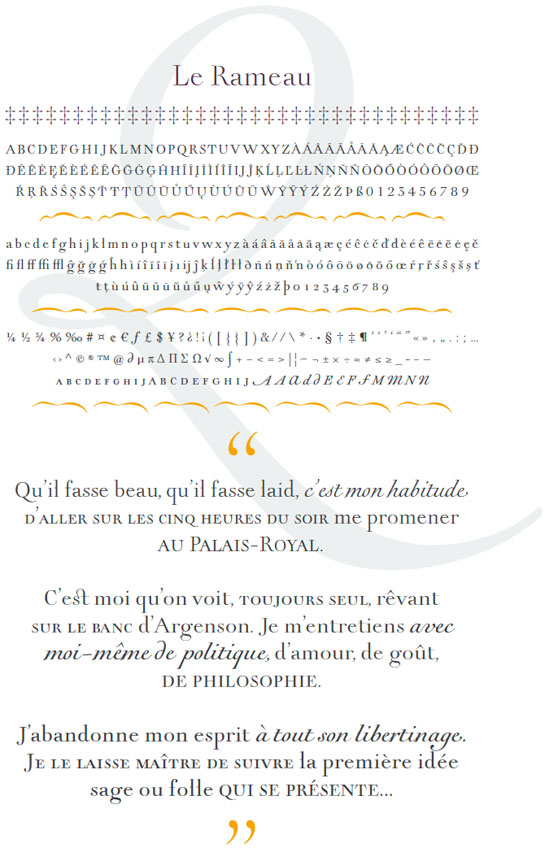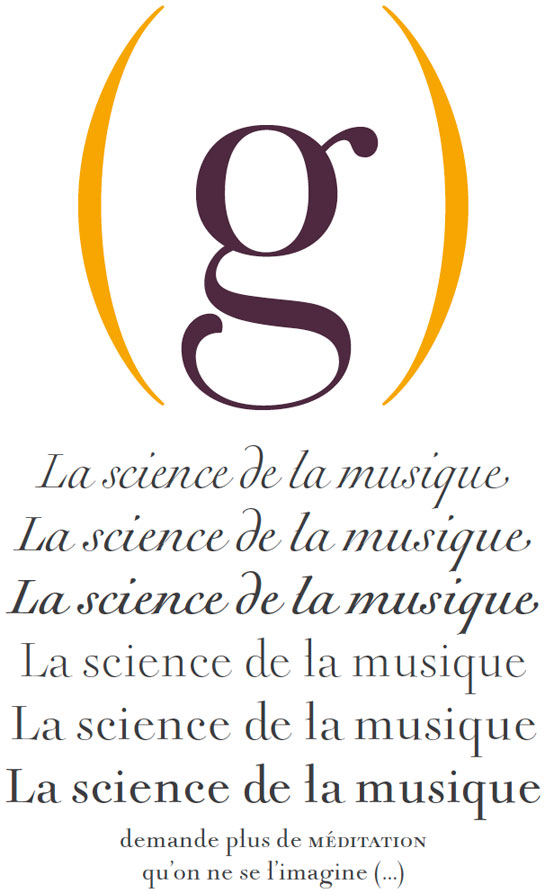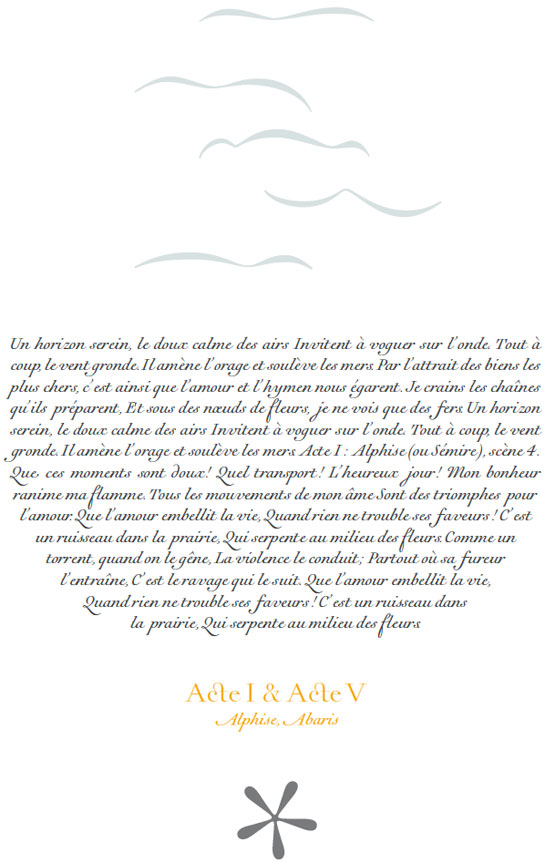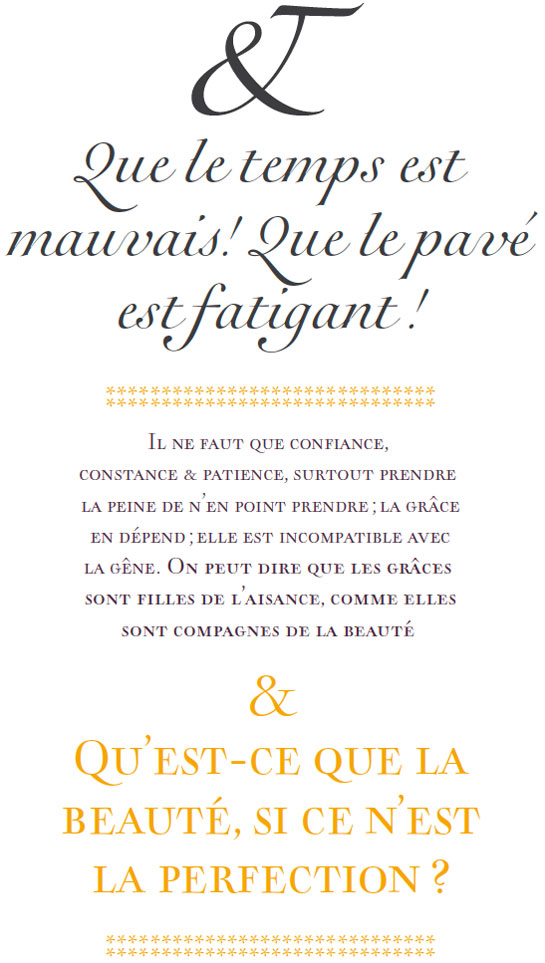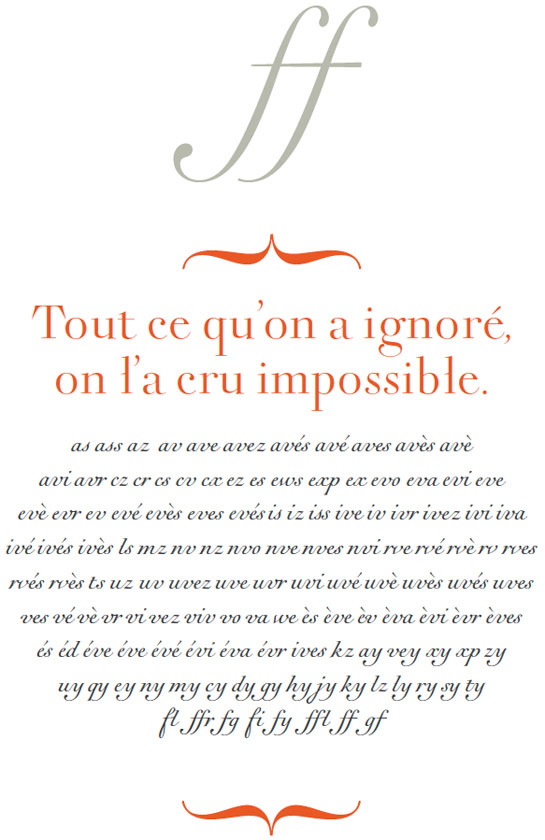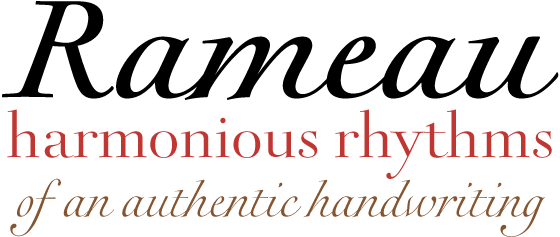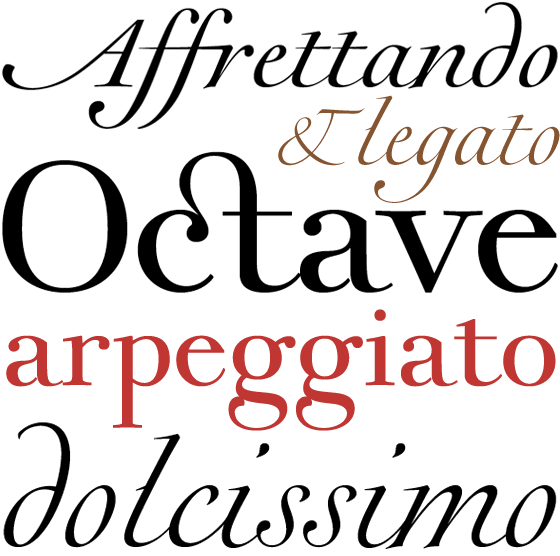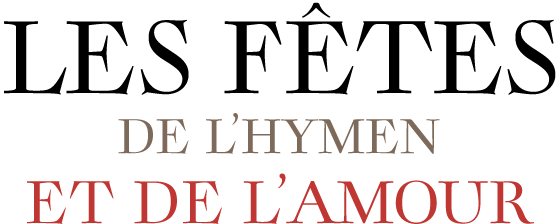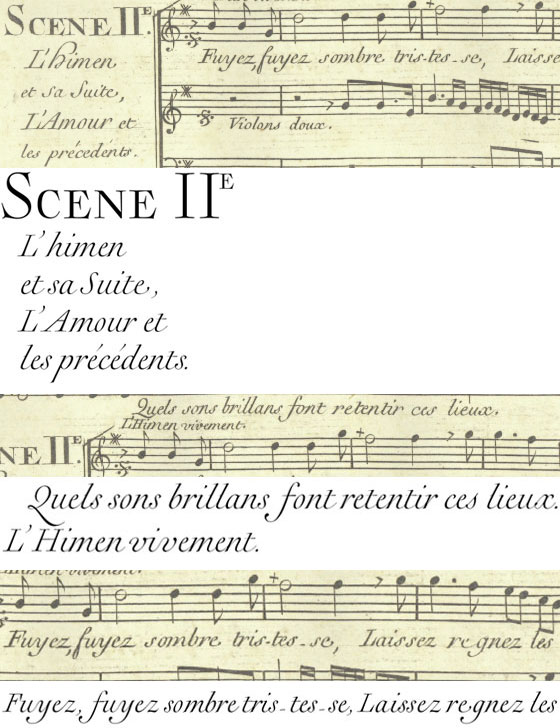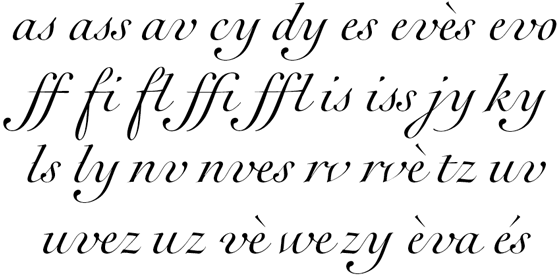
Rodzina fontów Rameau™ została zaprojektowana przez Sarę Lazarevic. Autorka rozpoczęła pracę od kursywy, której wzór zaczerpnęła z rękopisu opery “Les fêtes de l´hymen et de l´amour” dla której została skomponowana muzyka przez Jean-Philippe Rameau w 1747 roku w XVIII wieku. Partytura została opublikowana w formie odbitek z płyt miedzianych, które były ręcznie grawerowane, w przeciwieństwie do książek i innych publikacji, które drukowano w tamtych czasach z ruchomych czcionek ołowianych. W odmianach pochylonych kroju Rameau występuje wiele ligatur i są one typowe dla „stylu grawerskiego” tego okresu.
Przykłady wybranych ligatur z rodziny Rameau™ |
Fragment oryginalnego zapisu nutowego opery “Les fêtes de l´hymen et de l´amour” |
Rodzina Rameau wykazuje wiele harmonijnego rytmu związanego z oryginalnym rękopisem. Typowy dla krojów antykwy kontrast elementów składowych znaków dosłownie „bije w oczy”. Efekt ten jest wzmocniony przez zaznaczające się ostre zakończenia liter i wyraziste szeryfy wersalików.
Te bardzo czytelne i stylowe fonty mogą być używane do tworzenia prac wysokiej jakości książek, zaproszeń, menu i wszystkich innych rodzajów tekstów - gdziekolwiek chcielibyśmy osiągnąć wdzięk i elegancję Francji XVIII wieku.
Na górze - oryginalny zapis na partyturze - na dole ten sam tekst już jako font Rameau. |
Poniżej możesz zobaczyć, jak w odpowiednim kontekście typograficznym staje się widoczny pełny efekt elegancji fontów Rameau. Przykłady te zostały przygotowane przez Sarę Lazarevic i oferują wgląd w potencjał zastosowań tej uroczej antykwy.